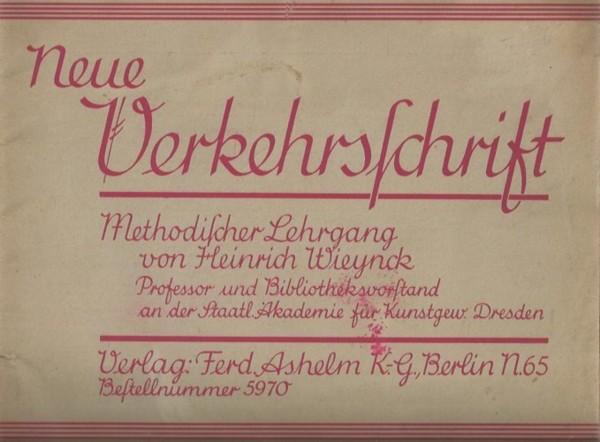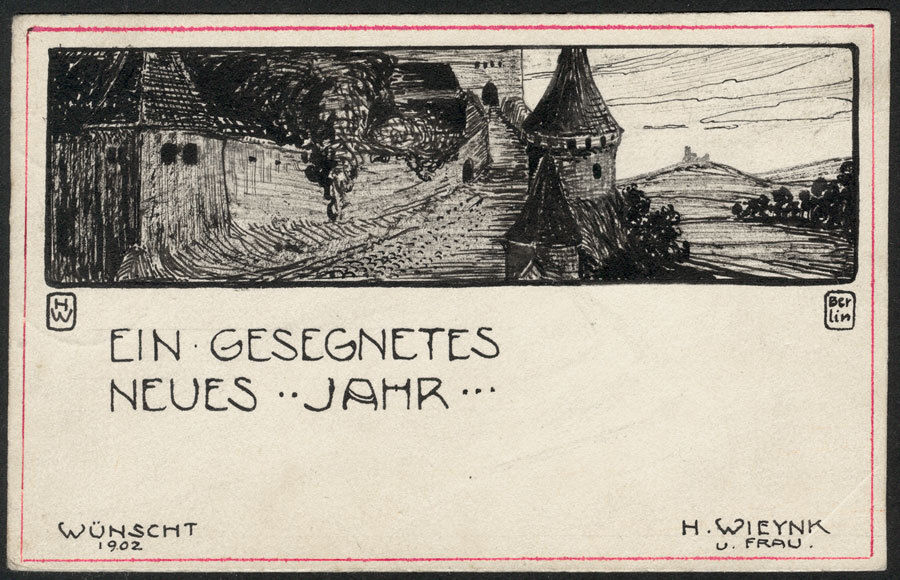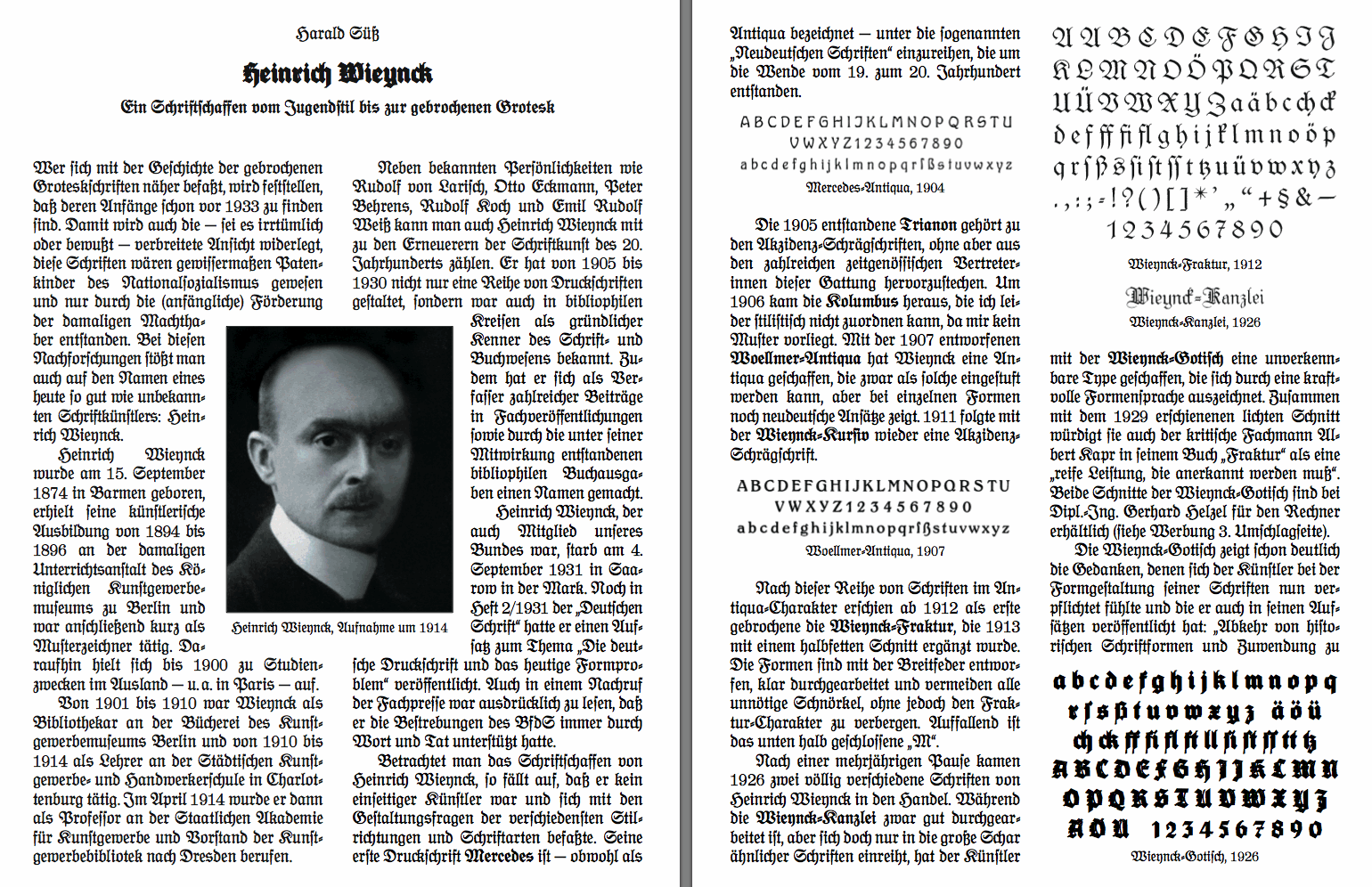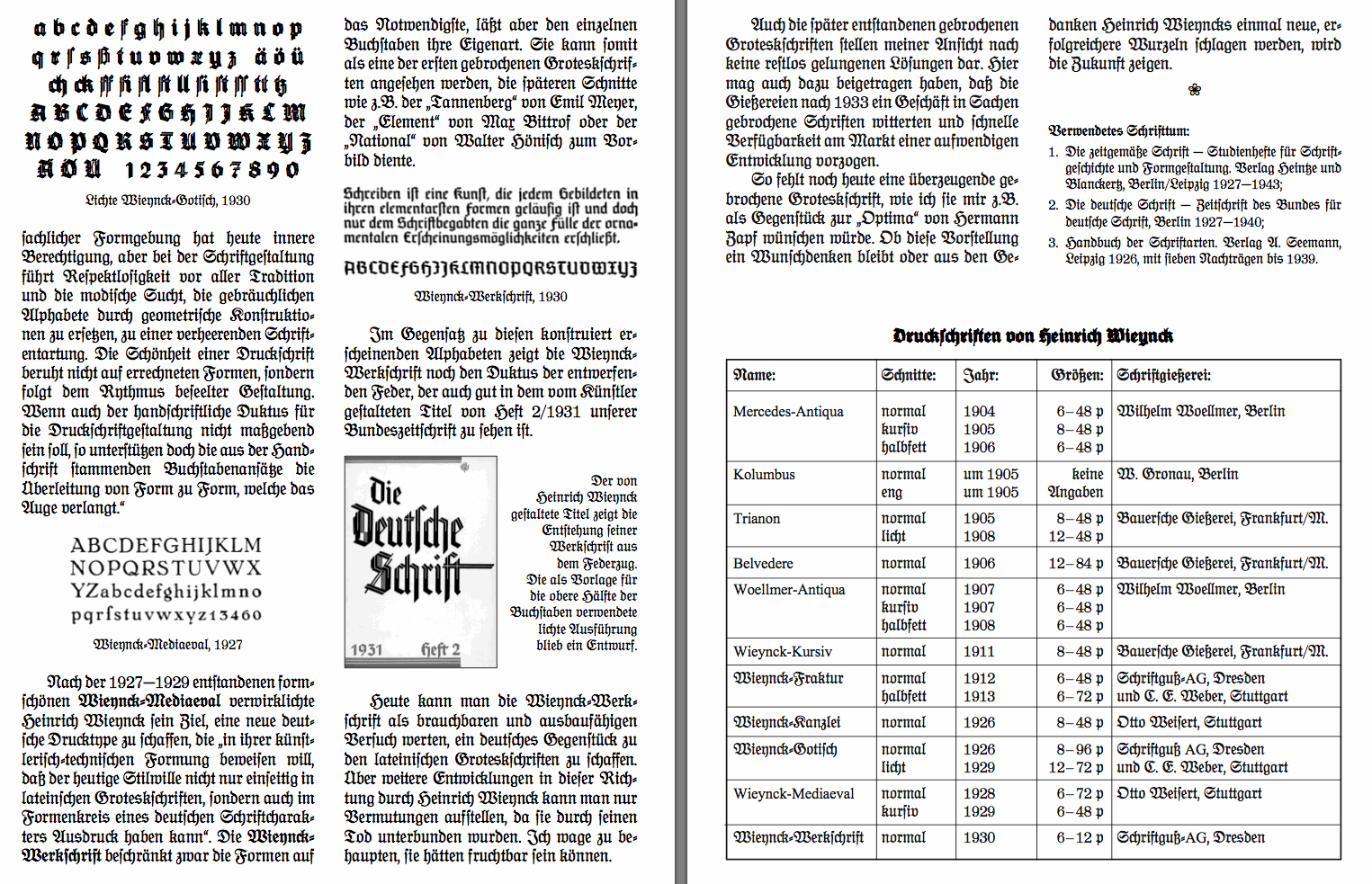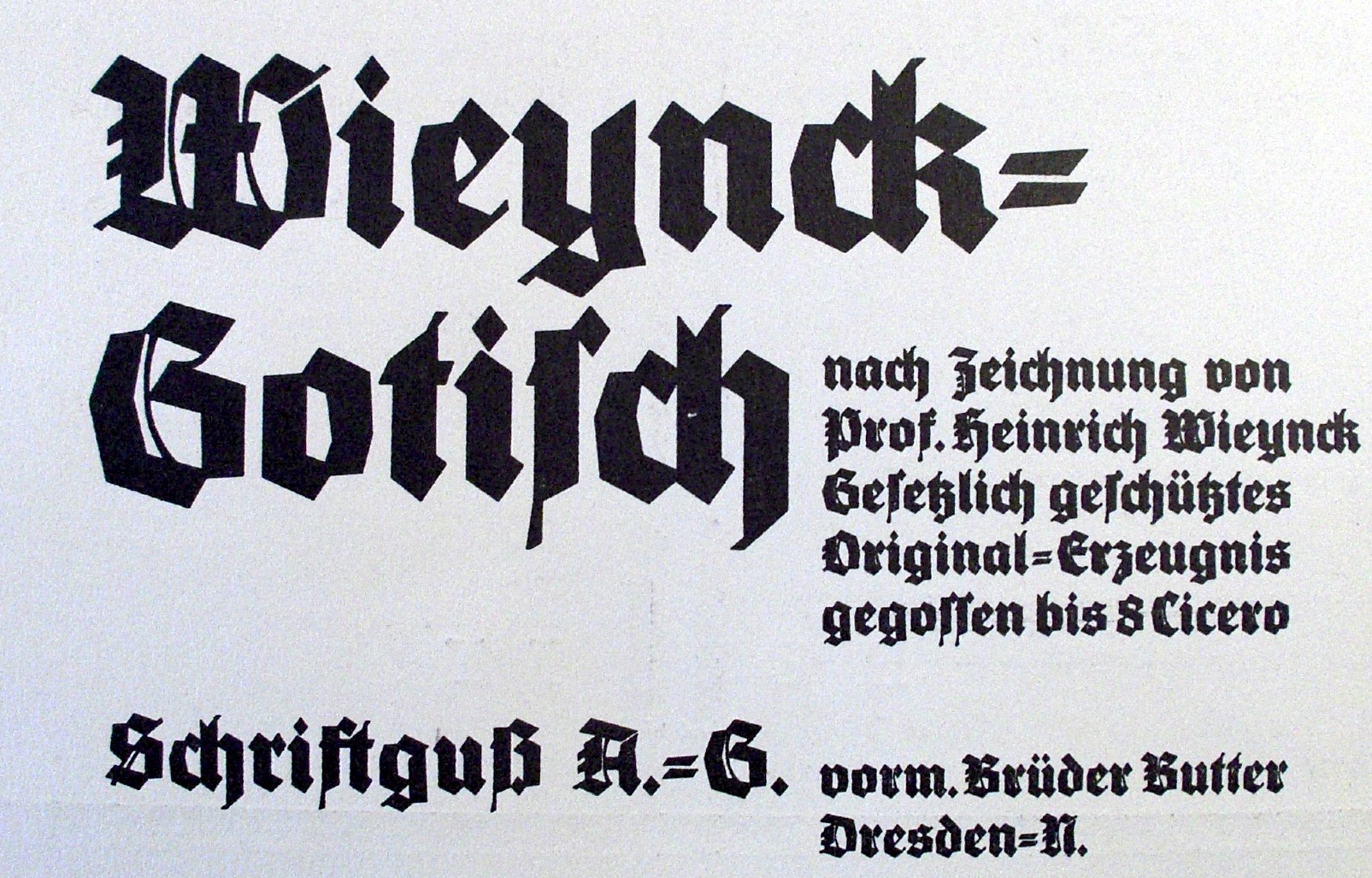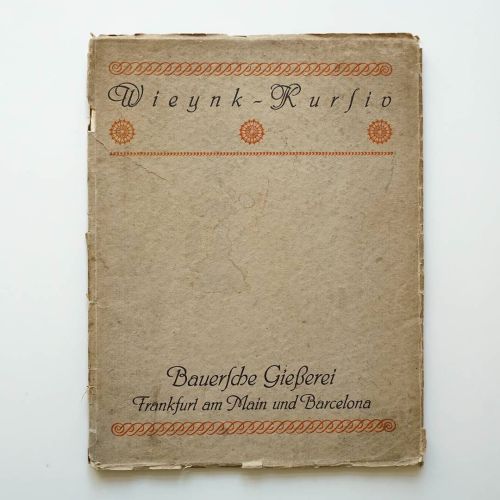
Wieynck oder Wieynk
Diverse Quellen geben den Namen mit c an:
auch Linotype und Klingspor.
Die Schriftmuster welche ich besitze (habe nicht alle geprüft) haben jedoch den Namen ohne c aufgeführt. Ich vermute mal das die Schreibweise mit c flasch ist, oder gab es damals eine Änderung im Namen?
das ist ja witzig. vielleicht hat er das c abgelegt als er im ausland gelebt hat?
er hat auch zwei neugotische frakturen entworfen Wieynck Gotisch mit mehren schnitten und die Wieynck Werkschrift. erstere mitten in der blütezeit der bauhaus-epoche, diese wurde 1926 veröffentlicht.
ich verlinke hier mal frech den artikel von Harald Süß, mit einem Zitat (?) von Wieynck:
"[...]Abkehr von historischen Schriftformen und Zuwendung zu sachlicher Formgebung[...]". ja, er spricht auch von 'Schriftentartung' in bezug auf geometrische Formen.
Sein berühmtester Schüler in Dresden war Jan Tschichold.
Es gibt diverse Texte von Wieyn(c)k, in welchen er seinen Unmut über die Prinzipien der Neuen Typografie äußert. Er hat außerdem ein kleines Regelwerk der Neuen Typografie verfasst, in welchem er die Thesen von Tschichold et al. aufs Korn nimmt.
Es sei erlaubt, den Thesen der Konstruktivisten einige eigene Thesen gegenüberzustellen, die den ›tiefsinnigen Gehalt‹ oder ›gehaltvollen Tiefsinn‹ der ersteren parodieren:
1. Eine Drucksache ist nach den Grundsätzen der Konstruktivisten zweckbetont, wenn ihre Mitteilung nur unter Schwierigkeiten gelesen werden kann.
2. Man verachte alles bisher geschaffene Schrift- und Ziermaterial, außer der mageren und fetten Venus-Grotesk und beschränke sich, entsprechend eigener Beschränktheit, auf das Viereck, den Kreis und das Dreieck, wenn man eine Drucksache organisieren will.
3. Man suche niemals die kürzeste, einfachste und eindringlichste Form für eine Aufgabe, sondern kompliziere durch raffinierte Textgruppierung und Wortzerreißung ihre Gestaltung bis zur Unleserlichkeit.
4. Man suche ferner die typographische Lösung in Form der Kreuzwort- und Bilderrätsel, indem man die Texte genügend oft neben-, über- und untereinander und in verwirrender Unordnung gestaltet, wobei die Windrose wertvolle Anregung geben kann.
5. Zur Erreichung sensationeller Wirkung in der neuen Typographie ist jede nichtssagende, abstrakte Form brauchbar, insbesondere führt die Anwendung fetter Linien und der unvermeidlichen Pfeilspitzen zu beglückenden Offenbarungen in der Flächengestaltung.
6. Die letzte Steigerung formalen Ausdrucks in der elementaren Typographie ist das unbedruckte, aber zweckbetonte Blatt Papier im geeigneten DIN-Format.
Aus: Neueste Wege der Typographie, Prof. Heinrich Wieynck, Archiv für Buchgewerbe und Gebrauchsgraphik, Heft 6 (1926), S. 379f.
Der wahrscheinlich bekannteste und am häufigsten zitierte Aufsatz von Heinrich Wieynck ist ›Die Wandlungen des Johannes‹ aus dem Jahr 1928. Darin äußerte er sich auch über die Zukunft und Bedeutung Tschicholds, und nahm dessen Entwicklung fast hellseherisch vorweg:
Das Buch Tschicholds [Die Neue Typographie] hat als interessantes Zeitdokument seinen Wert; es ist sicher ein Merkstein in der ganz natürlichen Entwicklung des Verfassers, die ich nicht als abgeschlossen ansehe, ja, die vielleicht in Zukunft den Johannes wieder zu Ehren bringen kann.
Aus: Die Wandlungen des Johannes, Heinrich Wieynck, Gebrauchsgraphik. Monatszeitschrift zur Förderung künstlerischer Reklame, Heft 7 (1928), S. 29.